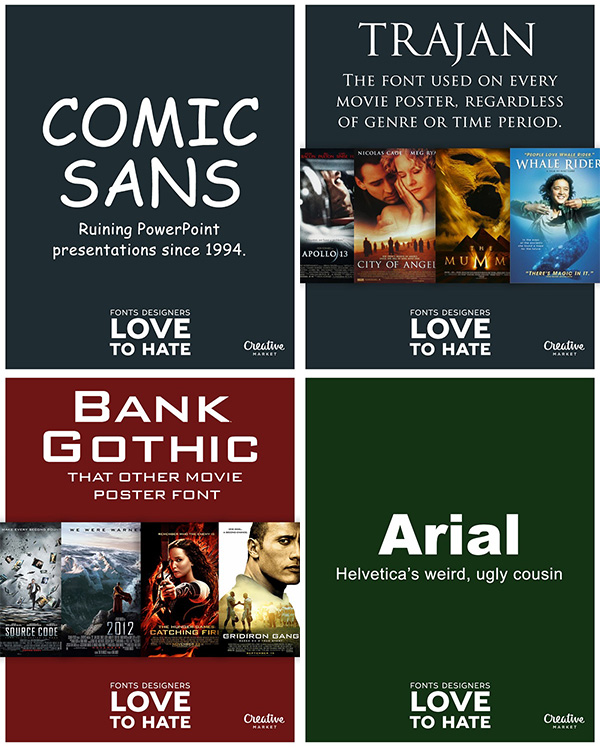
Todo el mundo tiene tipografías que le gustan más o menos, pero los diseñadores guardan un odio especial en su corazón para algunas de ellas. Y no solo hablamos de la Comic Sans o la Arial; también están ahí la Trajan (usada en todos los pósteres de película, da igual el género), la Bank Gothic (de los pósteres que no usan Trajan), las ilegibles Papryus y Zapfino o la atípica Lobster. Hay diez en Creative Market: 10 fonts that designers love to hate.
También están incluidas Helvetica y Times Roman, reinas de esa relación amor-odio que tan bien define el mundo del arte: todos los diseñadores las elogian hasta más allá del infinito pero también todos reniegan de usarlas.